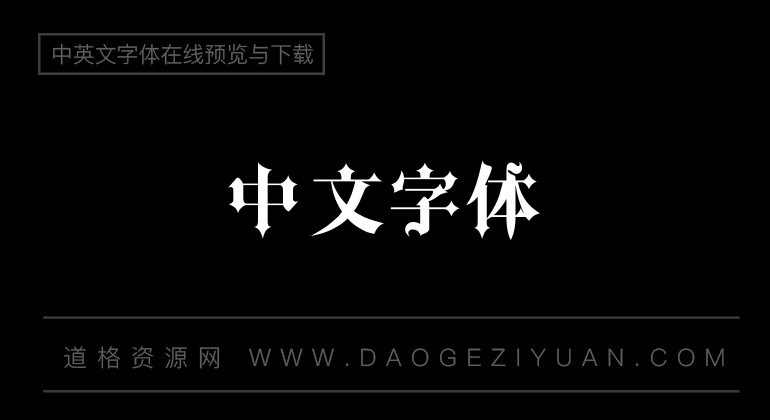
哥特式字体是一种古典风格的字体,由19世纪早期德国印刷师发明,主要用于书籍装帧和印刷。它的特点是有一定的视觉张力,字母表面有明显的凹凸感,特别是大写字母的拉伸,使字体看起来更有节奏感。哥特式字体的特点是粗细相间,线条粗细分明,有节奏感,给人以古典、古朴、高雅的感受,是文艺复兴时期最具代表性的字体之一。文件名:GeTeShiZiTi-1.ttf
哥特式字体是一款非常不错的手写艺术字体,具有很好的视觉感,适合于文化类的宣传设计、商业类品牌的广告和产品包装设计以及个性化文字排版等较多场景。